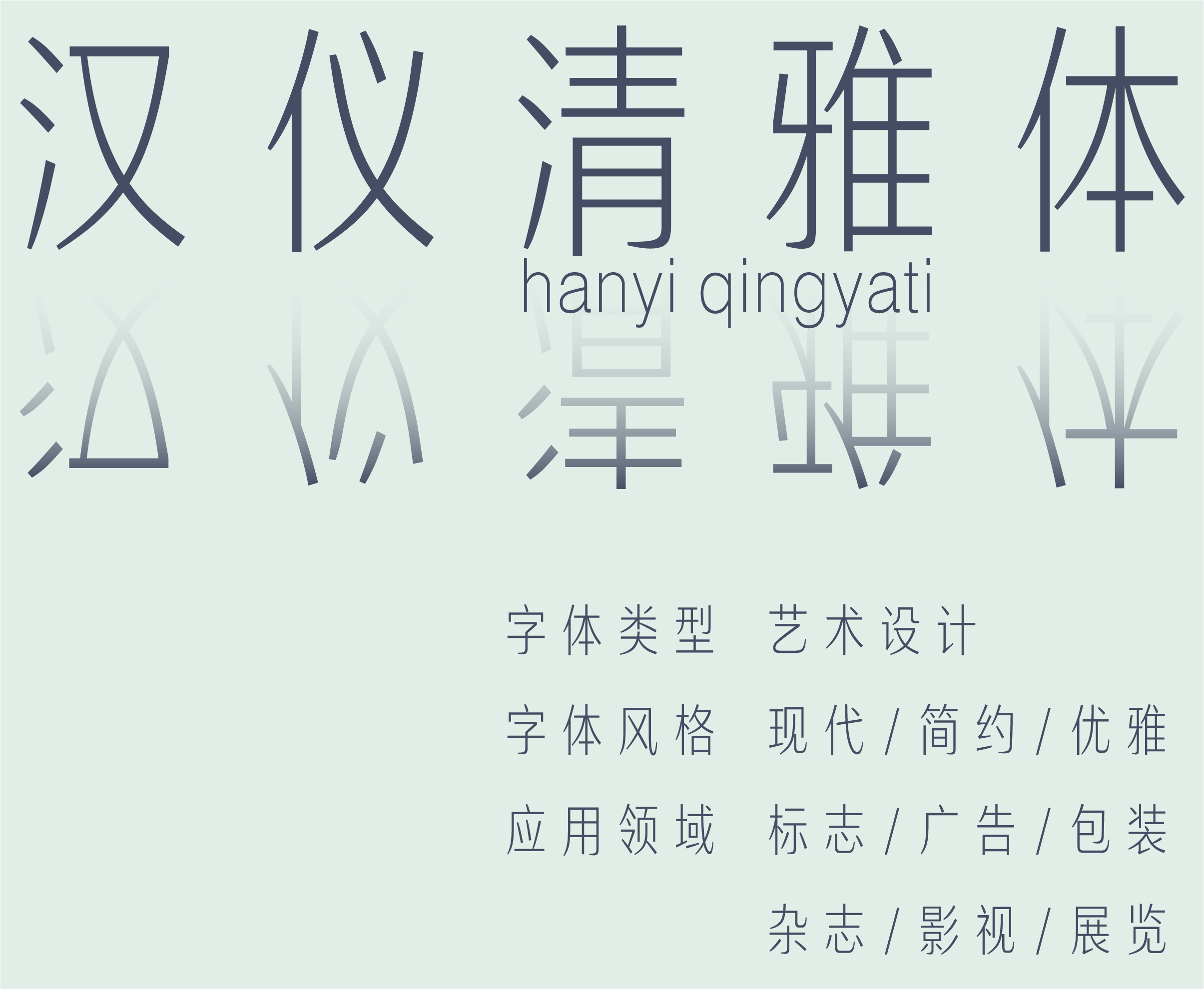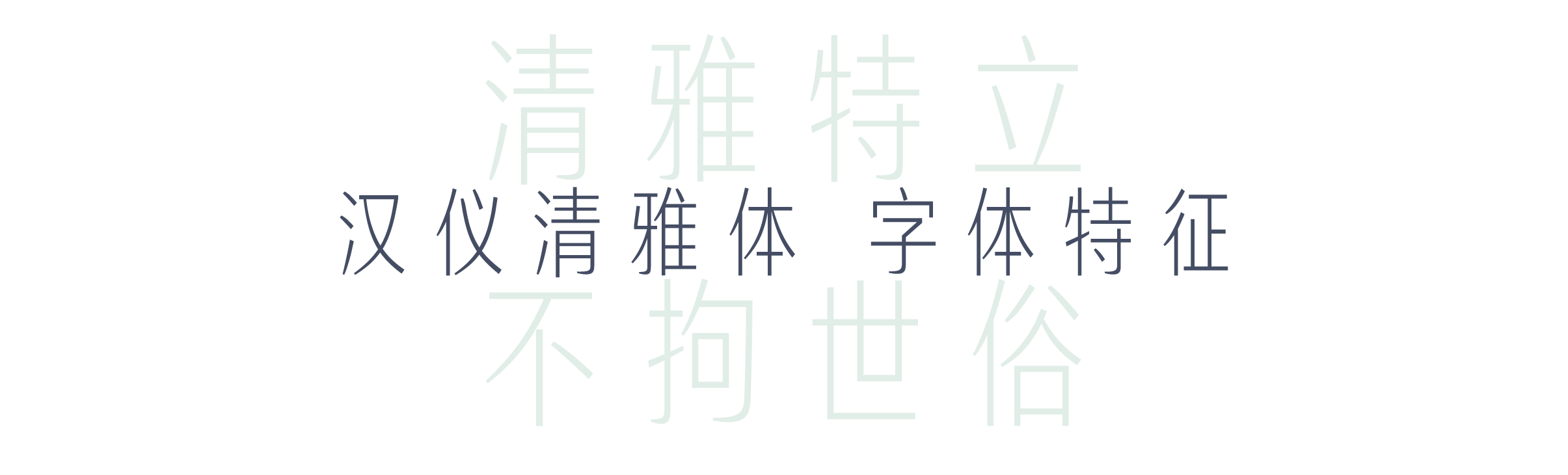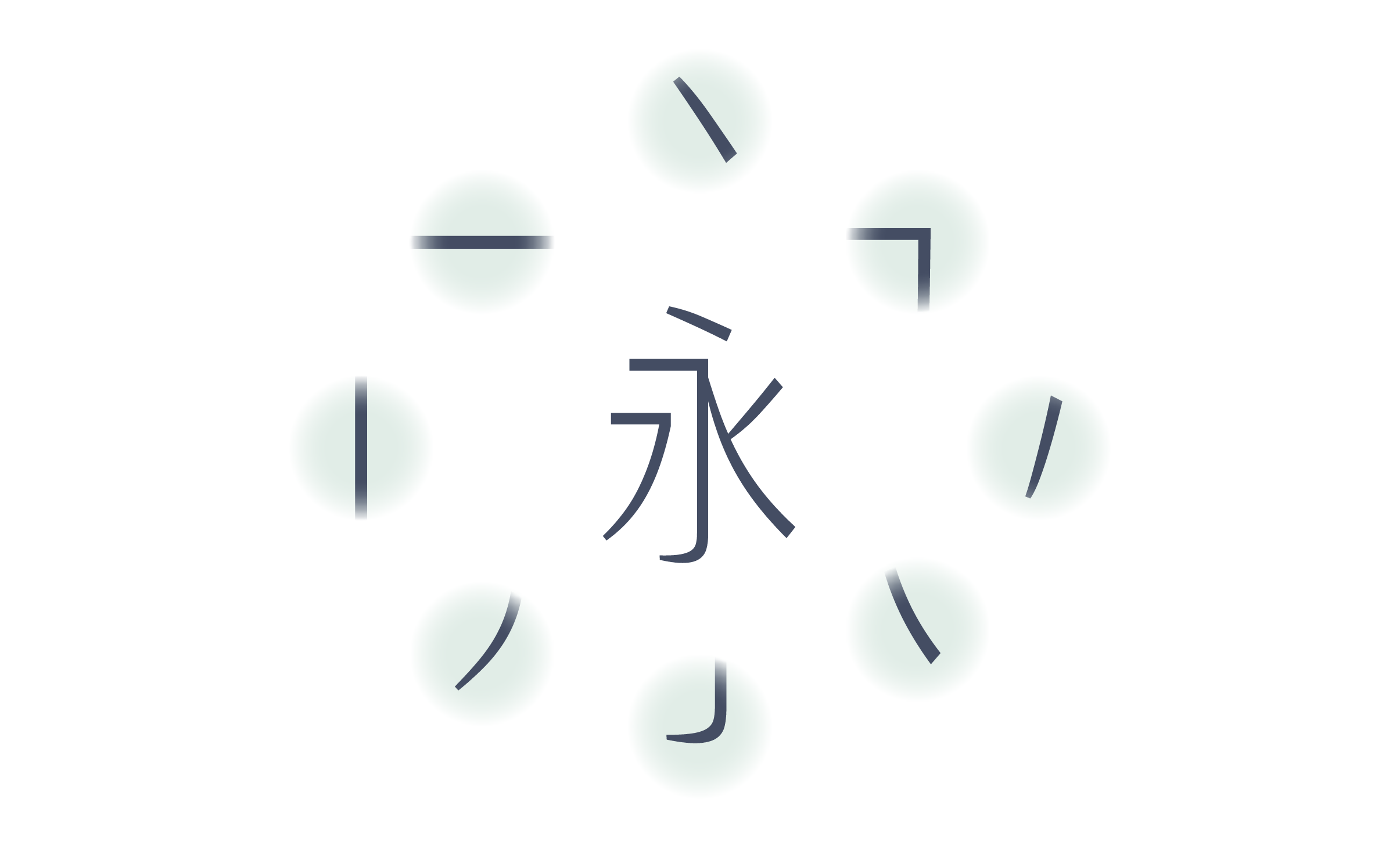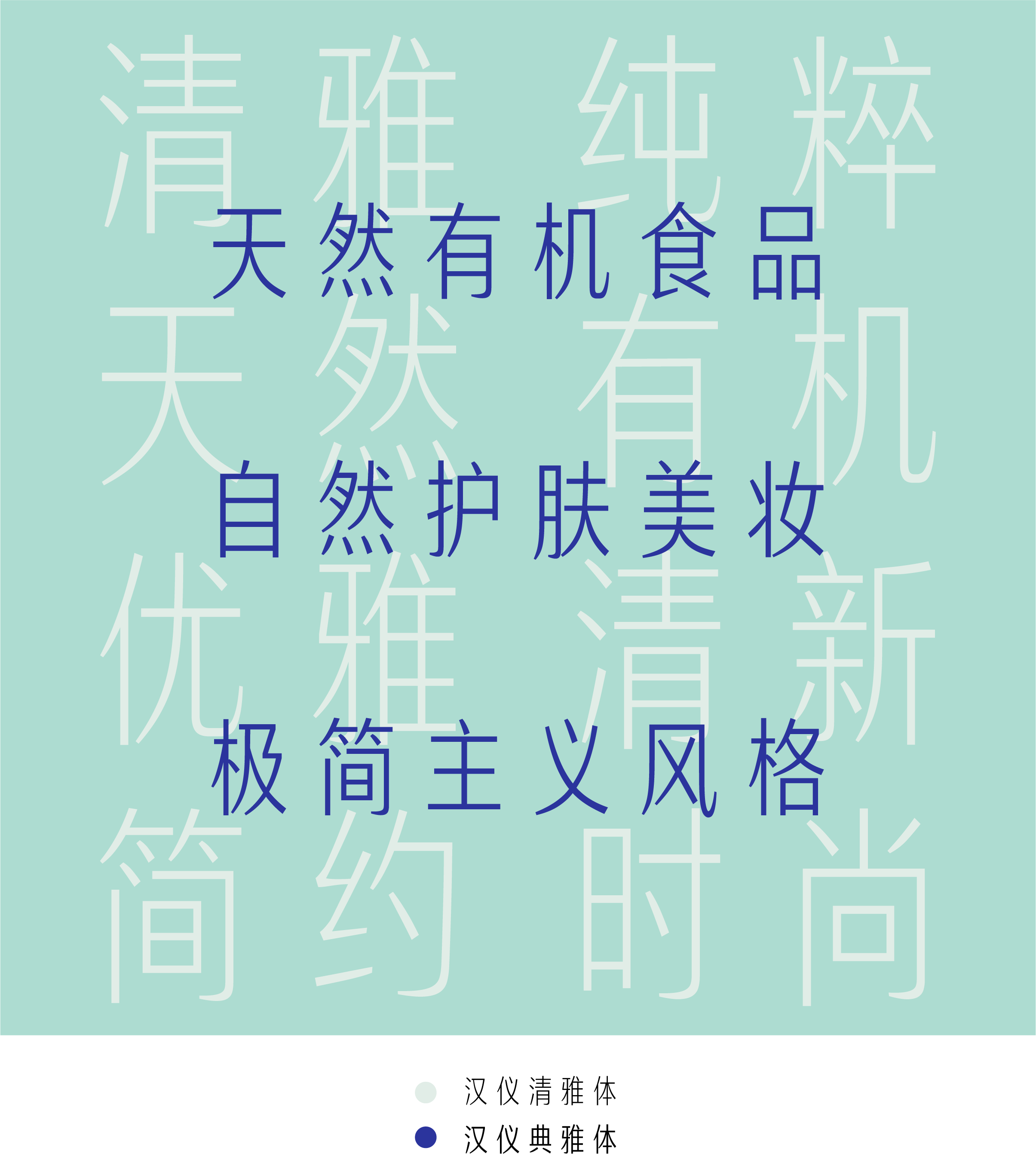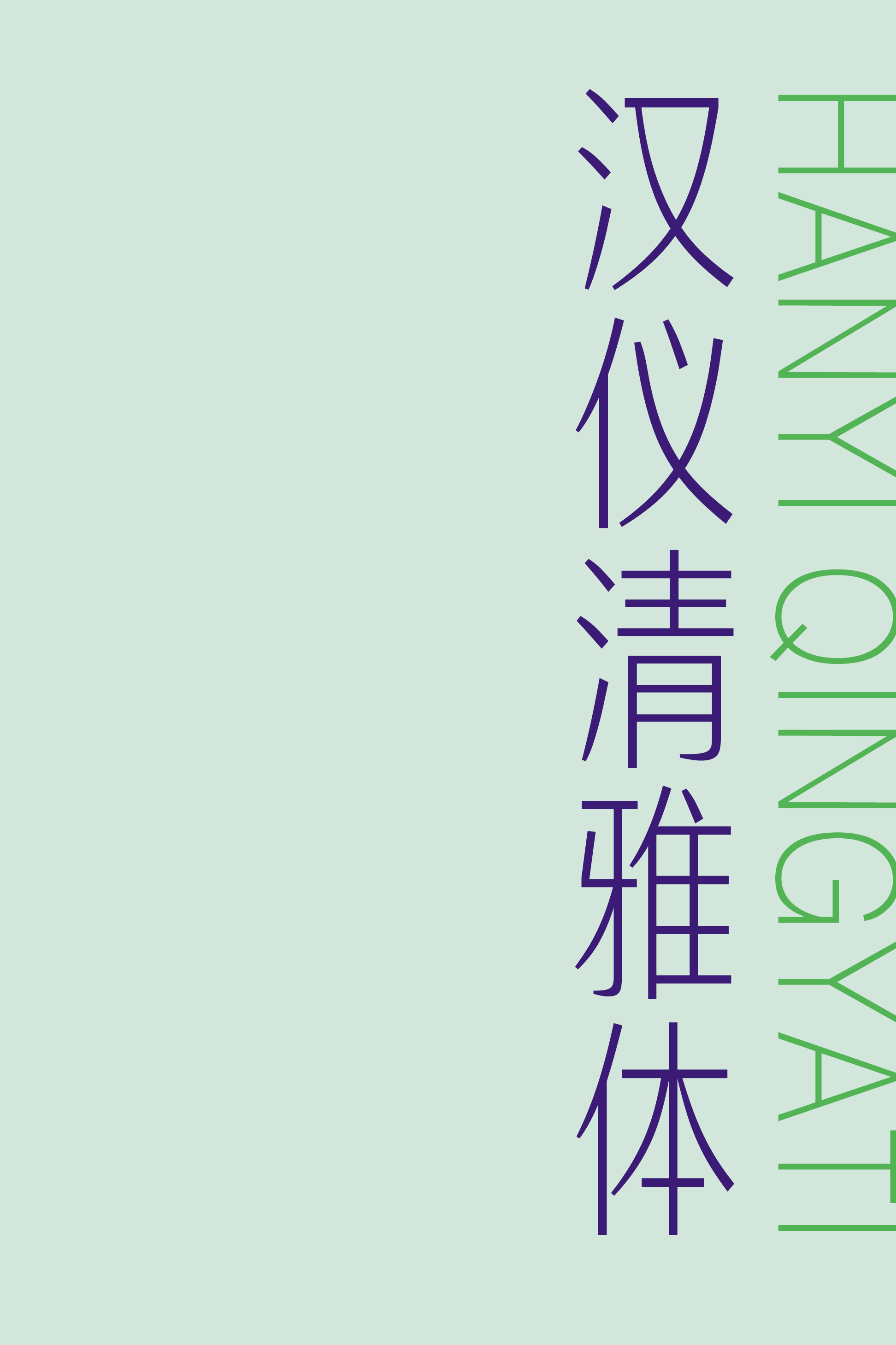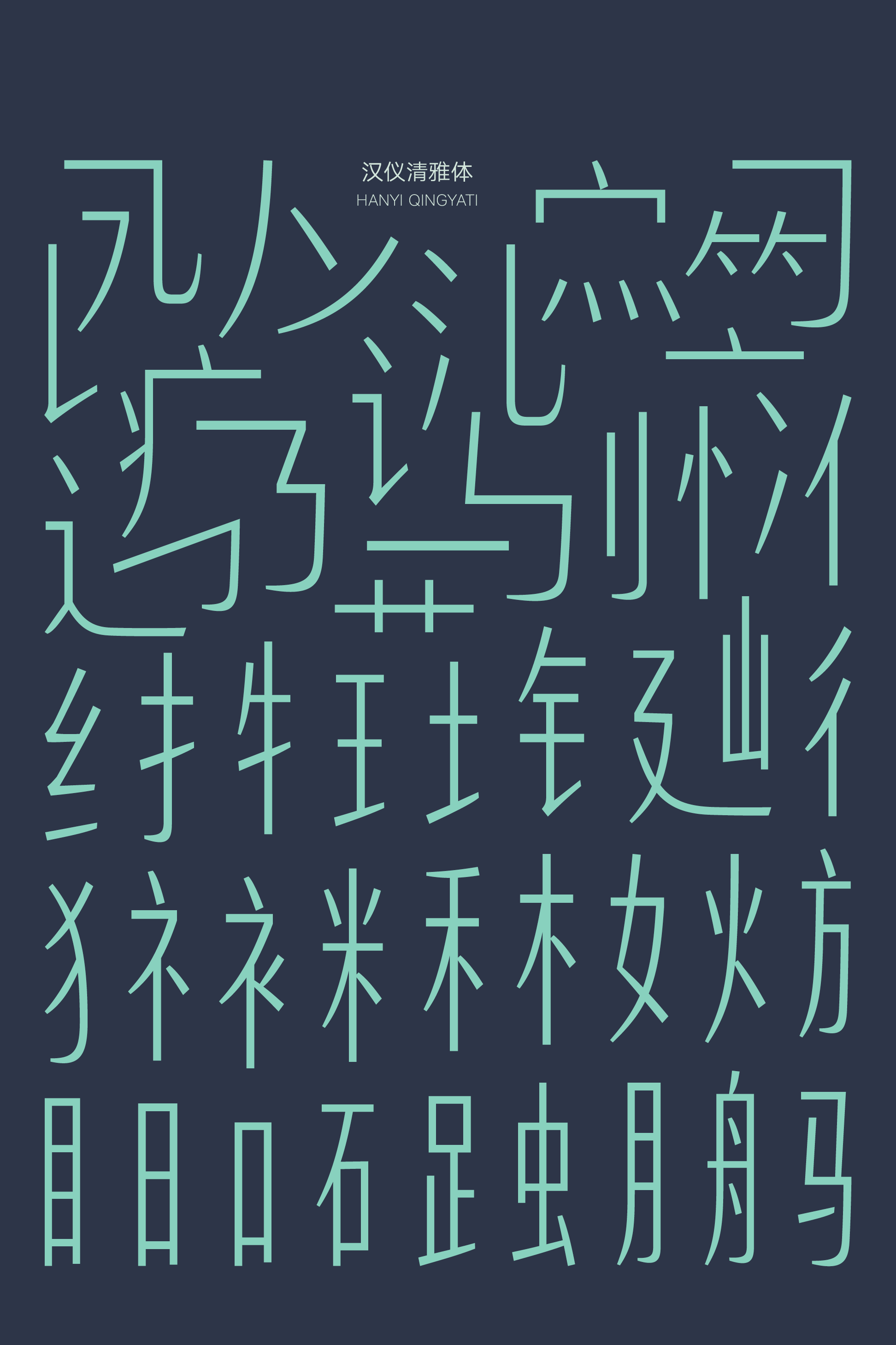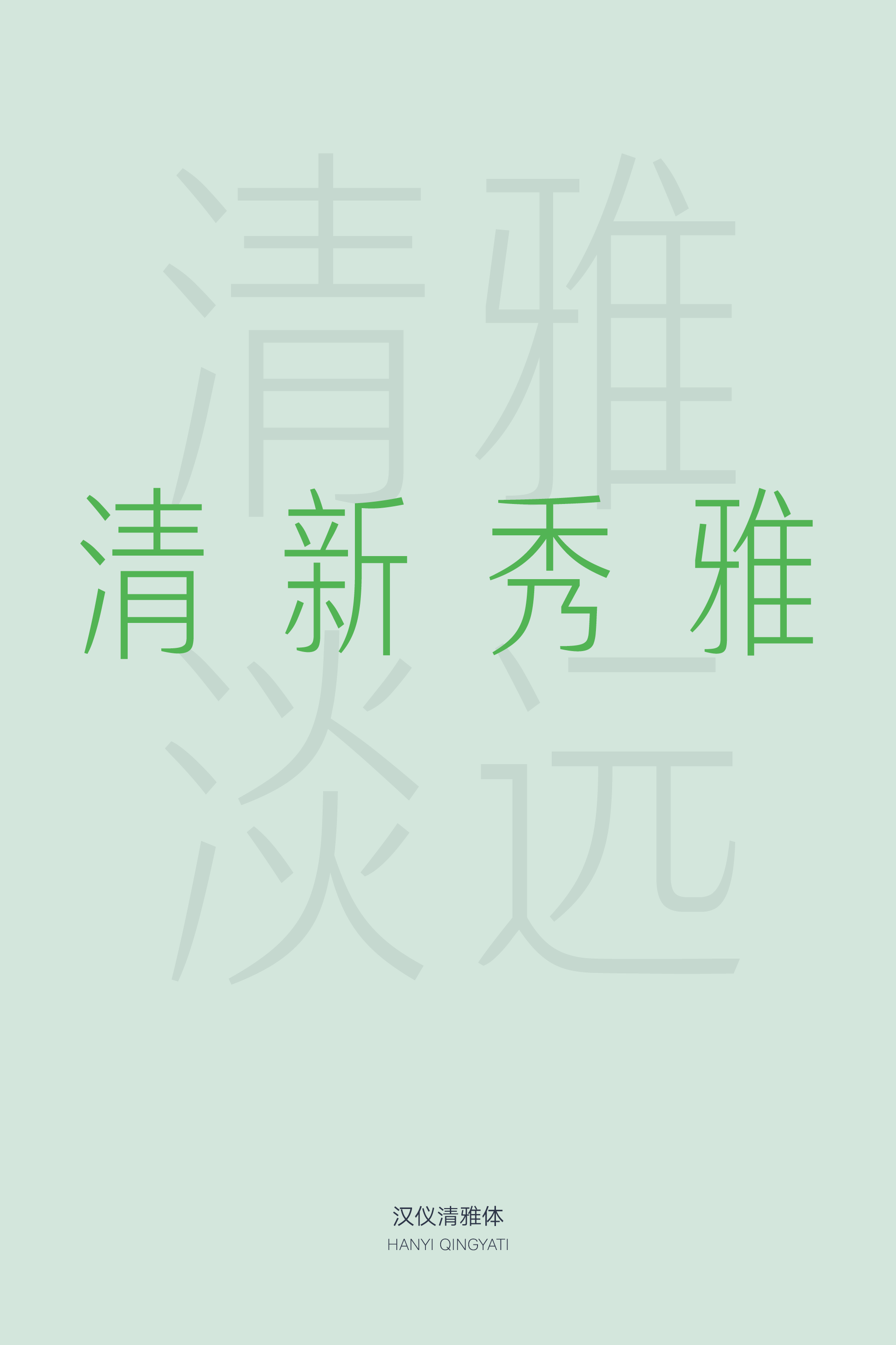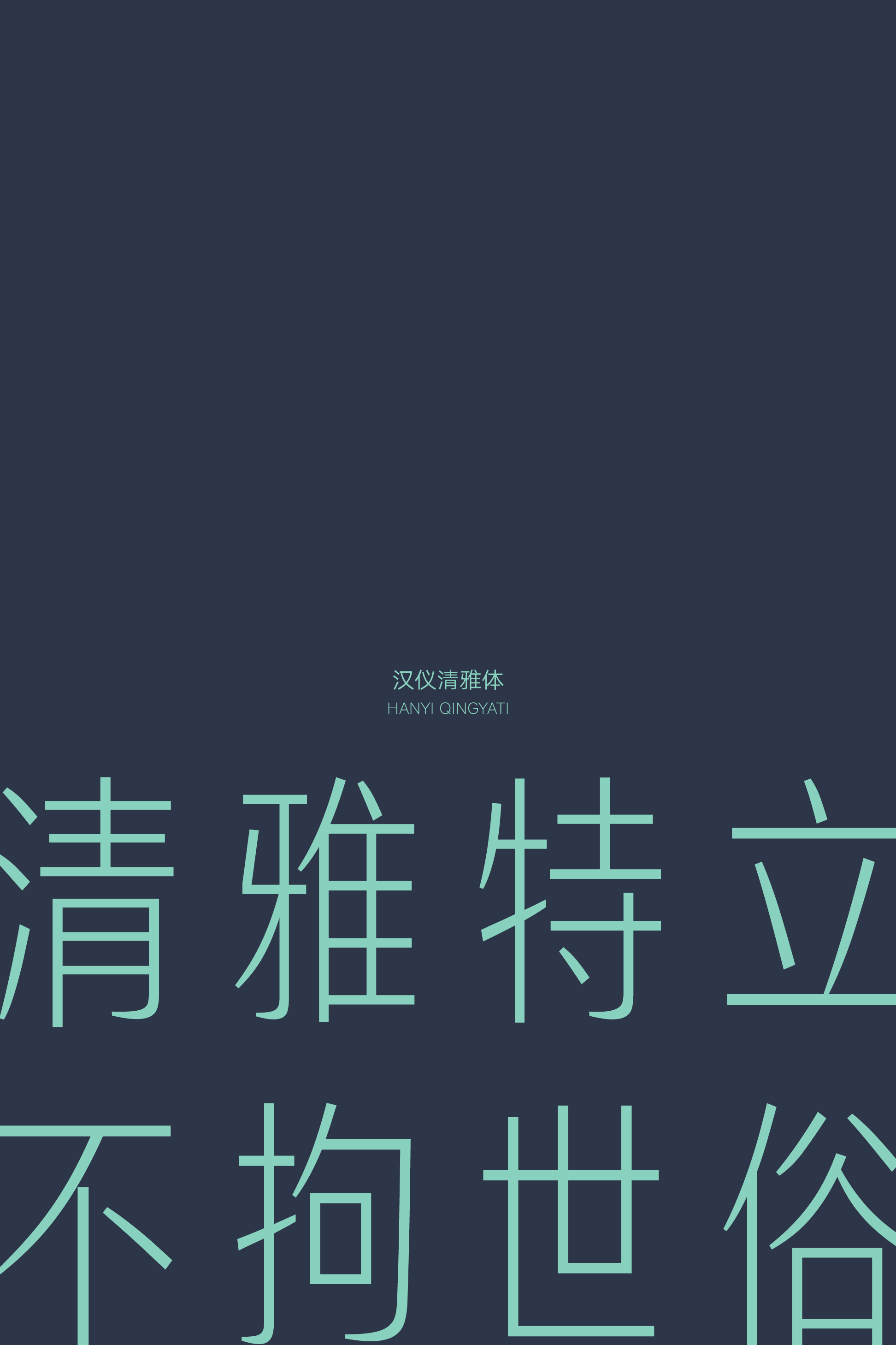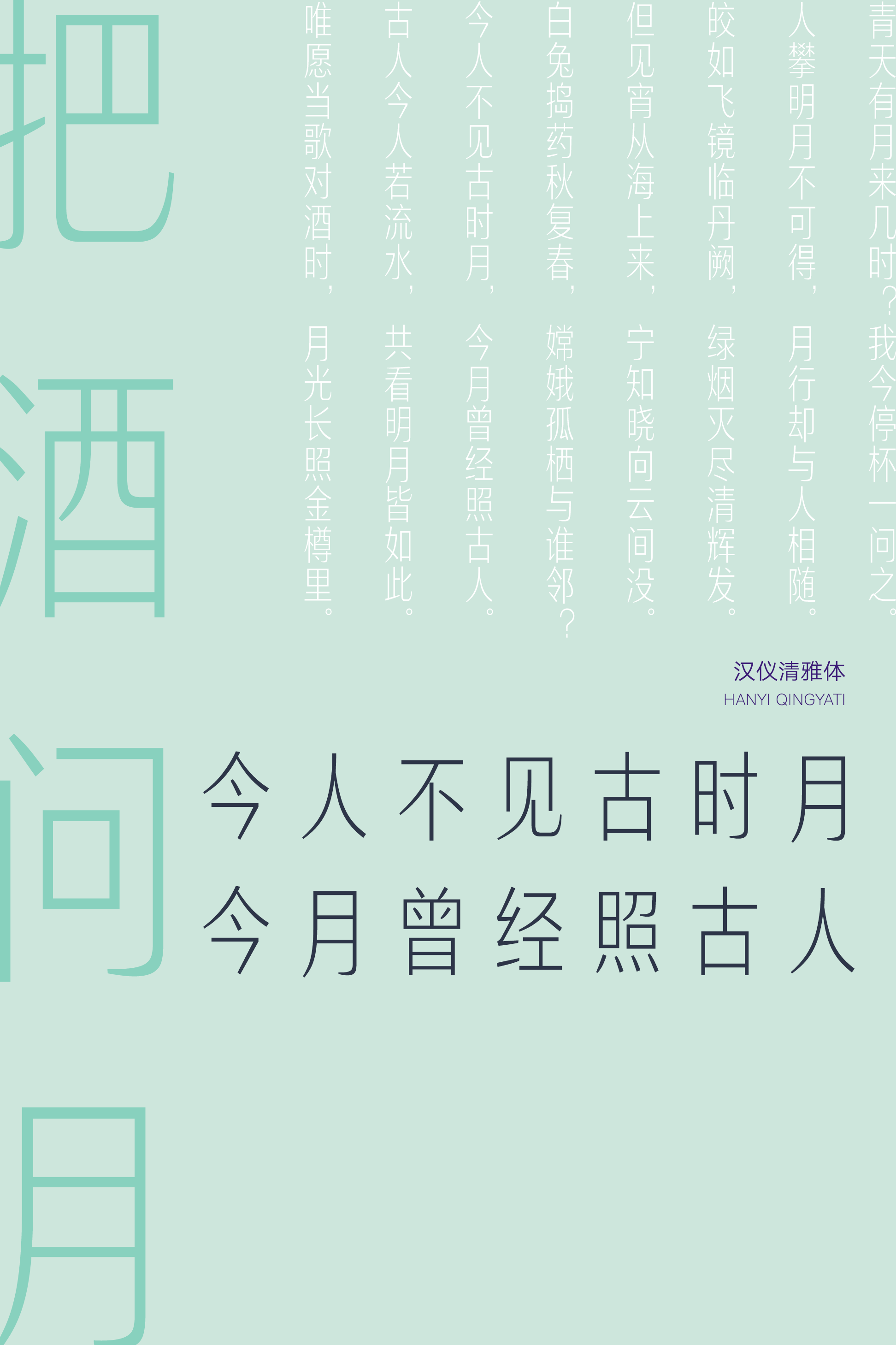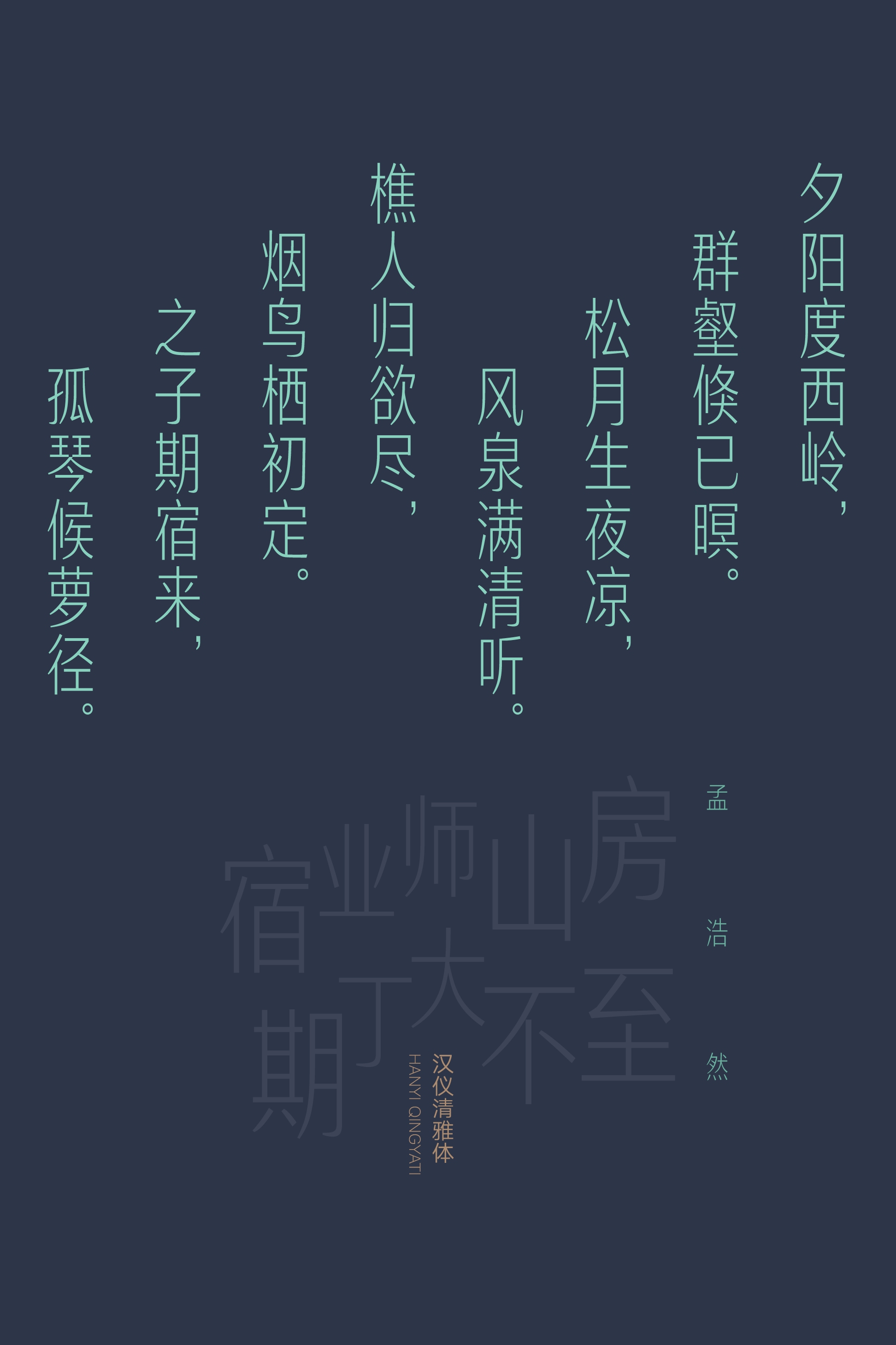
汉仪清雅体
汉仪清雅体,字形高挑,笔画纤细,气质清恬优雅。简约的笔画设计增强了字形的易读性,笔画弧度富有弹性,纤韧柔和。汉仪清雅体正如一阵清风,带来清新沉静的视觉享受,与天然有机、清新优雅、简约时尚的使用场景风格相符,可与线条稍粗的汉仪典雅体搭配使用,字里行间尽显优雅气质。
字形高挑,端正挺拔。
笔画简约,纤韧柔和。
可与线条稍粗的汉仪典雅体搭配使用,适合天然有机、清新优雅、简约时尚的使用场景。
汉仪清雅体|字体样张